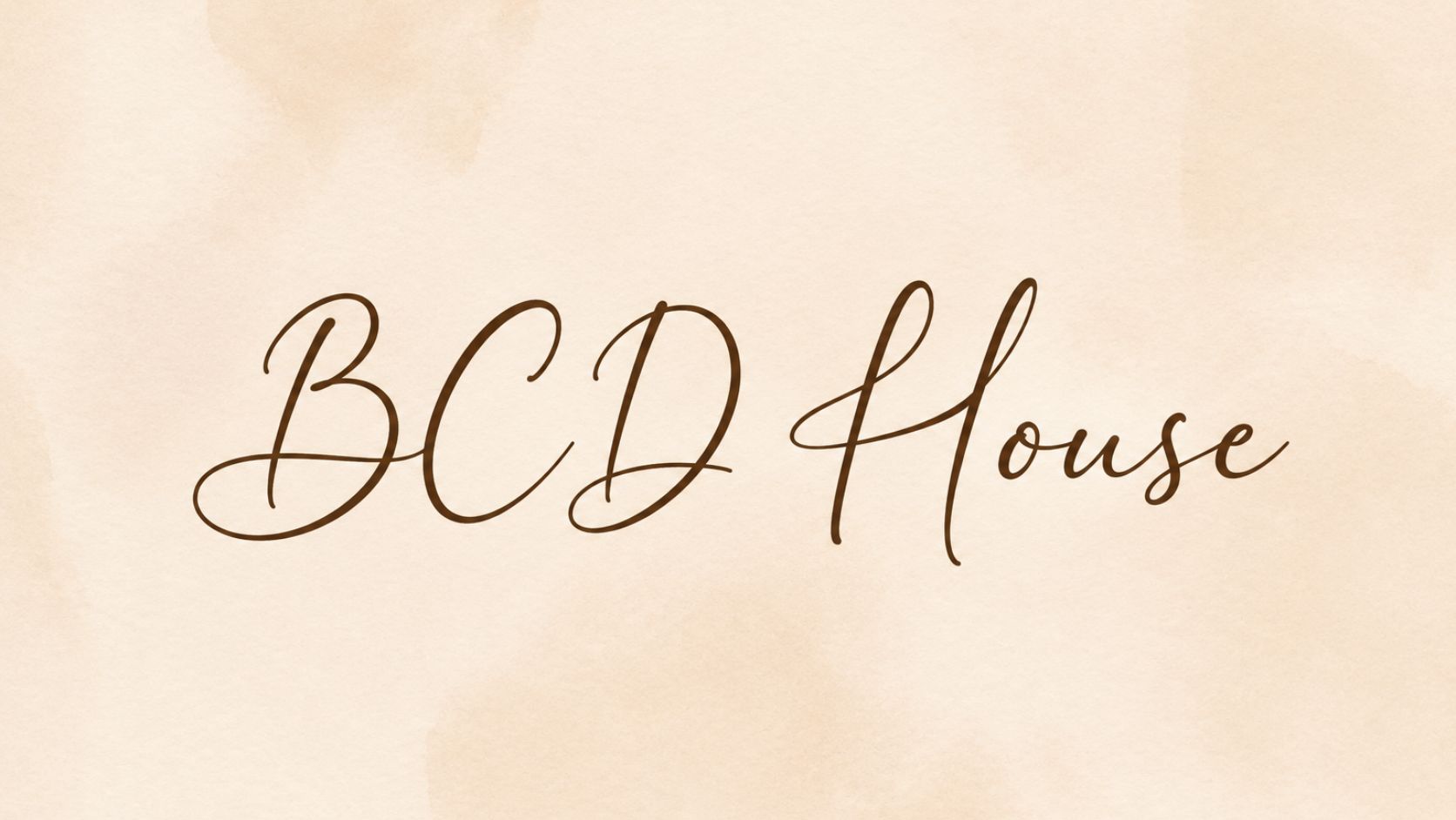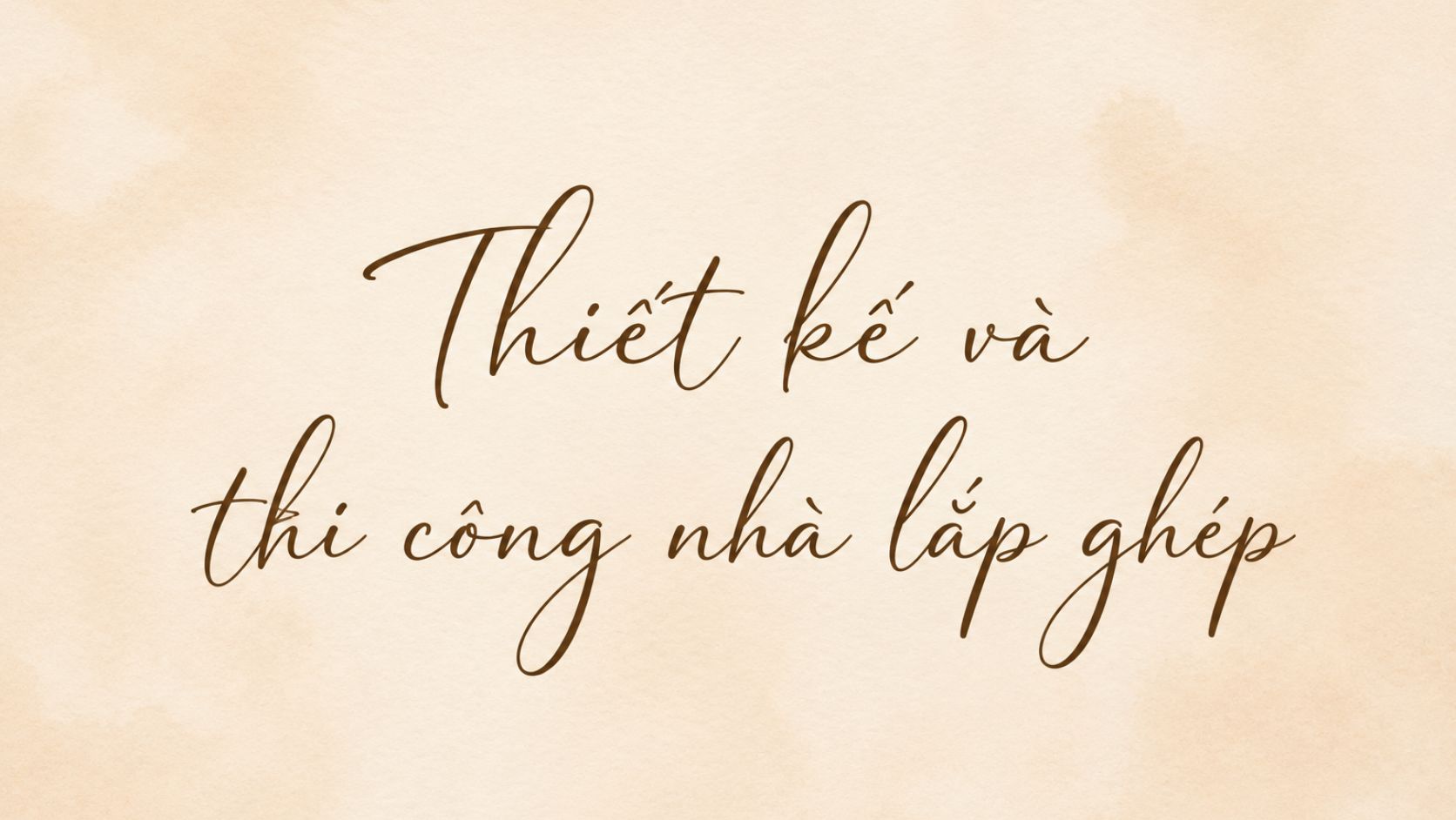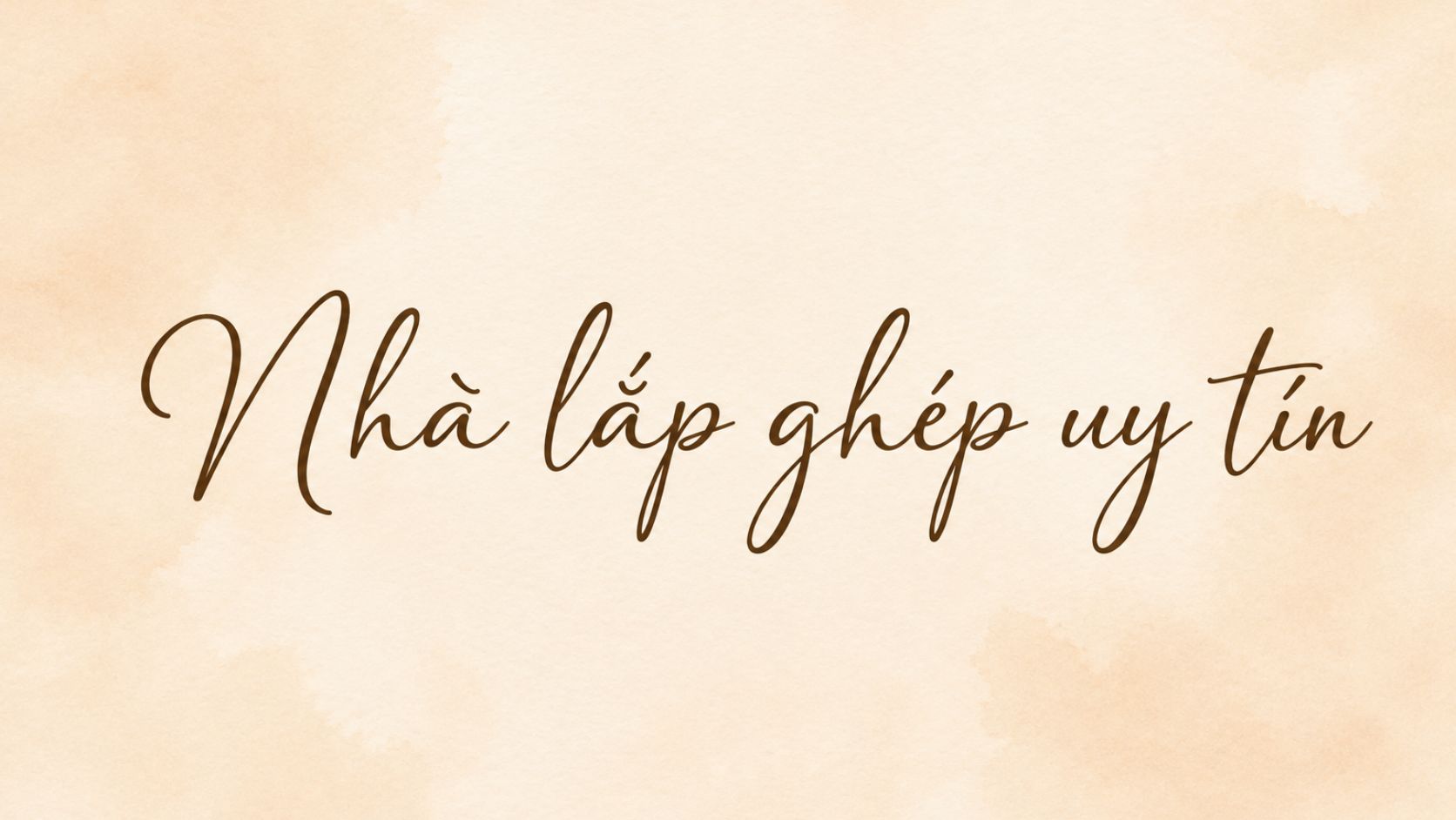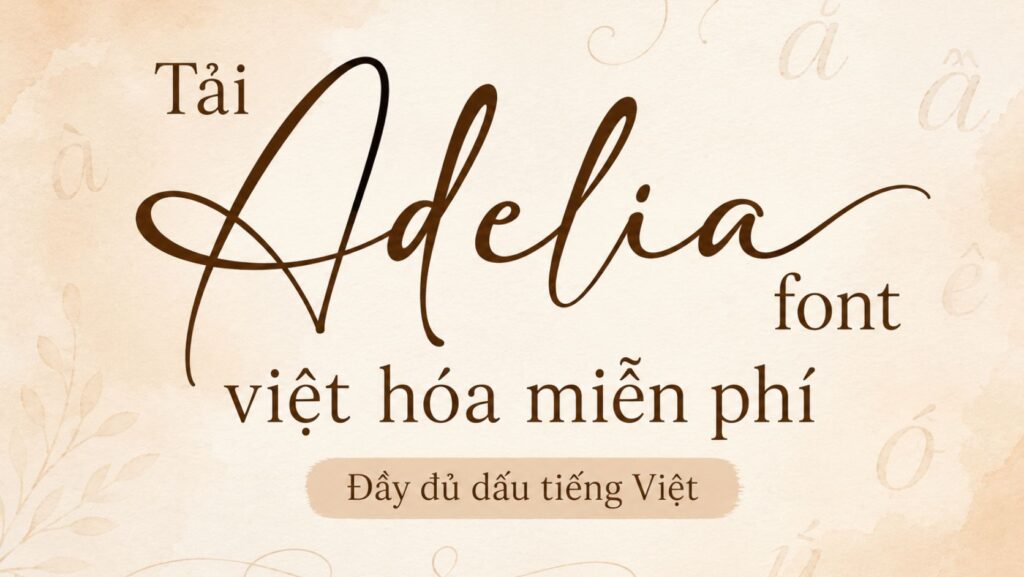
Adelia là bộ font chữ thuộc phong cách Script hiện đại với những đường nét uốn lượn mềm mại, phù hợp cho các thiết kế cần sự thanh lịch và bay bổng. Phiên bản Adelia font Việt hóa đã được tối ưu đầy đủ dấu tiếng Việt, giúp bạn dễ dàng ứng dụng vào các ấn phẩm đồ họa, bảng hiệu homestay hay trang trí nội thất mà không lo lỗi font. BCD House chia sẻ link tải font Adelia Việt hóa miễn phí cùng các lưu ý kỹ thuật để bạn triển khai thiết kế hiệu quả nhé!
Đặc điểm nổi bật của bộ font Adelia Việt hóa
Font Adelia gây ấn tượng mạnh nhờ cấu trúc chữ viết tay (handwritten) có tính tùy biến cao. Sự kết hợp giữa các nét nối tự nhiên và độ nghiêng vừa phải tạo nên cảm giác gần gũi nhưng vẫn giữ được sự chuyên nghiệp trong các sản phẩm thiết kế hiện đại.
Phong cách Script hiện đại và tính ứng dụng cao
Khác với các dòng font script cổ điển thường gây khó đọc, Adelia tập trung vào sự thông thoáng của các ký tự. Điều này giúp font chữ vẫn đảm bảo được tính thẩm mỹ khi in ấn trên các chất liệu khác nhau như gỗ, alu hay decal. Người dùng có thể sử dụng Adelia cho tiêu đề poster, thiệp mời, hoặc logo thương hiệu cần điểm nhấn mềm mại.
Độ tương phản nét thanh nét đậm tinh tế
Điểm đắt giá của Adelia nằm ở sự chuyển đổi mượt mà giữa các nét lên và nét xuống. Độ tương phản này tạo ra hiệu ứng thị giác tốt, giúp câu chữ có chiều sâu hơn. Đặc biệt, bản Việt hóa đã được tinh chỉnh để các dấu thanh (huyền, sắc, hỏi, ngã, nặng) không đè lên các nét móc, giữ nguyên vẻ đẹp nguyên bản của font chữ.
Tại sao nên sử dụng font Adelia trong thiết kế kiến trúc và nội thất?
Trong lĩnh vực kiến trúc, đặc biệt là các công trình nhà lắp ghép và homestay container, việc lựa chọn font chữ nhận diện đóng vai trò quan trọng trong việc định hình phong cách. Font Adelia thường được các kiến trúc sư tại BCD House ưu tiên nhờ sự tương phản thú vị giữa kết cấu thép cứng cáp của nhà lắp ghép và nét chữ uốn lượn mềm mại.
- Bảng tên phòng và biển chỉ dẫn: Nét chữ Adelia tạo cảm giác chào đón, thư giãn cho khách lưu trú tại các khu nghỉ dưỡng.
- Số nhà và bảng tên công trình: Sử dụng font này để cắt CNC hoặc uốn nổi đèn neon sẽ tạo ra điểm nhấn sang trọng cho mặt tiền nhà phố hoặc văn phòng lắp ghép.
- Phối cảnh nội thất: Đưa font Adelia vào các bản vẽ concept giúp khách hàng dễ hình dung về một không gian sống có gu và tính cá nhân hóa cao.
Lưu ý: Font Adelia phù hợp khi dùng làm tiêu đề (Heading) hoặc đoạn văn ngắn từ 1-2 câu. Với các đoạn văn bản dài hoặc hồ sơ kỹ thuật, bạn nên kết hợp Adelia với các font không chân (Sans Serif) để đảm bảo trải nghiệm đọc tốt nhất.
Lưu ý: Font Adelia có nhiều ký tự thay thế (Glyphs) rất đẹp. Để sử dụng được các nét móc dài hoặc ký tự trang trí, bạn nên sử dụng các phần mềm hỗ trợ bảng Glyphs như Adobe Illustrator hoặc CorelDraw để khai thác tối đa vẻ đẹp của bộ font này.
FAQs – Câu hỏi thường gặp về font chữ Adelia
3. Có thể dùng font này để làm biển số nhà lắp ghép không?
Rất phù hợp. Adelia có nét chữ rõ ràng, khi cắt laser trên gỗ hoặc kim loại sẽ tạo nên vẻ thẩm mỹ hiện đại cho các mẫu nhà lắp ghép BCD House.